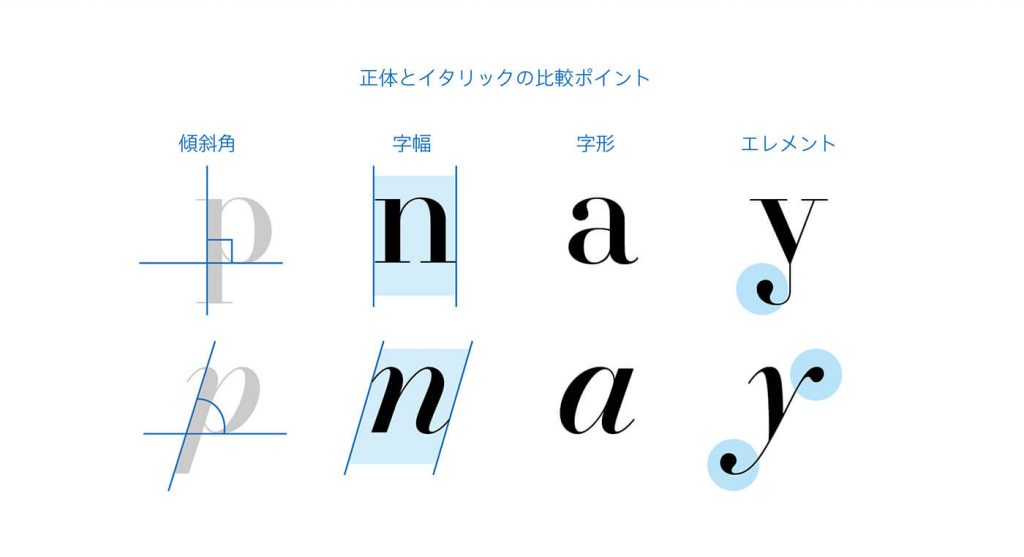
欧文イタリック04「イタリックのデザインプロセス」
書体デザインのプロセスはデザイナーによってそれぞれ異なりますが、正体とイタリックを持つ書体ファミリーでは正体のデザインがある程度定まった段階でイタリックのデザインを行うことが多いです。これは二つのスタイルを同時に組み立てていくよりも、一方のデザインの大枠が決まっていた方がもう一方のデザインを行う際に二者の差を比較しやすいためです。
傾斜角、字幅、字形、起筆や終筆といったパーツの形など、いくつかのポイントを中心に、正体との差を比較検討して行きます。
濱明朝イタリックでは、既にリリースされていた濱明朝の正体をベースにイタリックのデザインを組み上げて行きました。